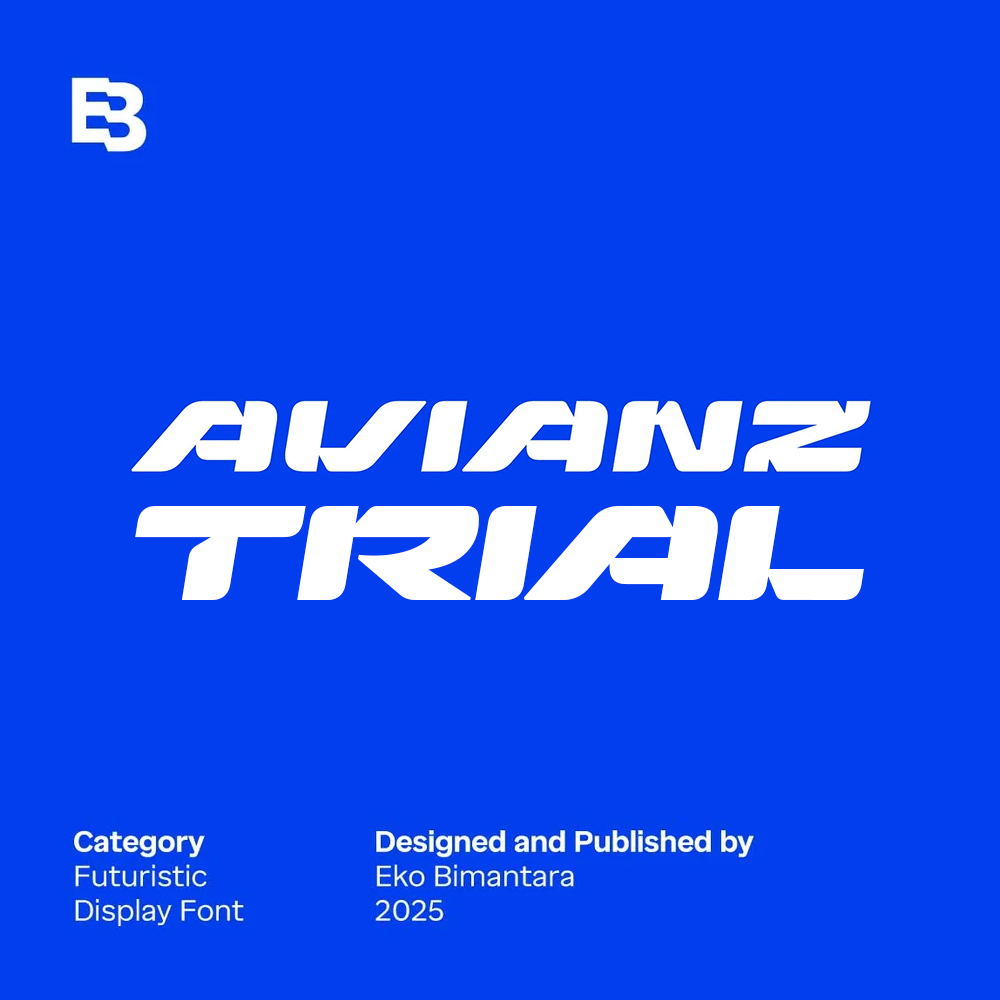
فونت پرمیوم و انگلیسی Avianz Trial Font یک فونت نمایشگر بزرگ و آینده نگر است که با زیبایی شناسی، جسورانه و دقیق طراحی شده است که…
فونت پرمیوم و انگلیسی Avianz Trial Font یک فونت نمایشگر بزرگ و آینده نگر است که با زیبایی شناسی، جسورانه و دقیق طراحی شده است که آن را برای پروژه های دیجیتال و تکنولوژیکی عالی می کند. طراحی زیبا و مدرن آن با موضوعاتی مانند تجارت، هواپیما، تجارت و طراحی معاصر سازگار است.